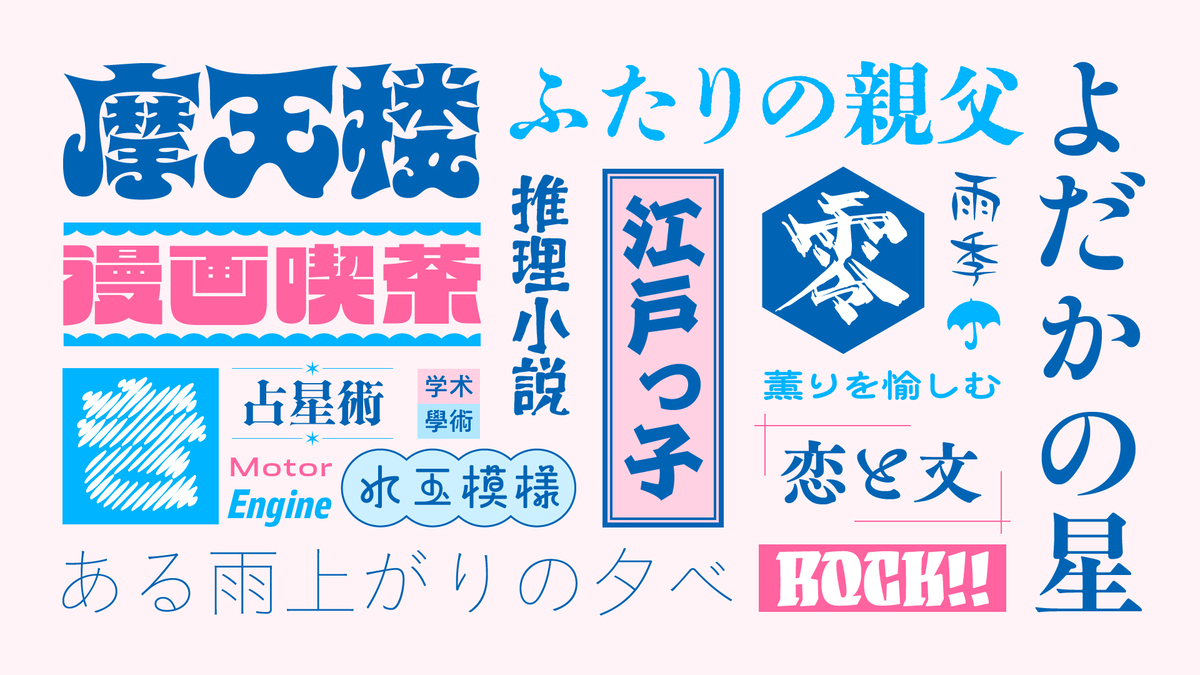
Webフォントサービス「TypeSquare」に世界観づくりにぴったりな和文デザイン書体やグローバルな情報発信にも対応できる多言語書体などの2024年度新書体を追加
モリサワは2024年10月15日から、WebフォントサービスTypeSquareに、世界観づくりにぴったりな和文デザイン書体のほか、グローバルな情報発信にも対応できる多言語書体、写研フォントなど2024年度新書体として160書体を追加したことを発表した。
2024年度新書体には、サイケデリックなアートや音楽からインスパイアされた極太の「虹蛸天国(にじたこてんごく)」のほか、丸い輪のような装飾が楽しげな印象を与える「はるかぜ」、江戸文字からインスパイアされた「てやんでぇ」など、世界観づくりにぴったりなデザイン書体をリリース。
さらに書家による毛筆の文字が元となった「花氷(はなごおり)」など、華やかな筆文字系デザイン書体の選択肢が広がる。
明朝体には、2023年にリリースした「欅(けやき)明朝 Oldstyle」の見出し書体「欅見出明朝」や、人気の「秀英にじみ」シリーズから「秀英にじみ初号明朝」などを新たに追加。
ユニークなファミリー展開が特徴の「Heavy」シリーズなど、デザインに彩りを加える特色豊かな欧文書体にも注目。
そのほか、グローバルな情報発信にも対応できる多言語フォントがより充実する。
オールドスタイルのゴシック体「A1ゴシック」に簡体字や繁体字が、欧文スーパーファミリー「Role」にインドと東南アジアの主要な種類の文字に対応する多言語展開ファミリーが、それぞれ登場。
また、ヒラギノフォントには人気書体「こぶりなゴシック」の最も細いウエイトW0を追加。
加えて、株式会社写研の代表的な書体をOpenTypeフォントとして改刻した「石井明朝」「石井明朝オールドスタイルかな」「石井ゴシック」のほか、「ゴナ」「ナール」などのバリエーション豊かな見出し書体を提供する。
UD学参丸ゴシック N Regular / Bold / Heavy
〈ヒラギノフォント〉
こぶりなゴシック W0
〈写研〉
石井明朝 L / R / M / B
石井明朝オールドスタイルかな L / R / M / B
石井中明朝 M
石井中明朝オールドスタイル大がな M
新聞特太明朝 E
石井ゴシック L / R / M / B / EB
石井中ゴシック M
ゴナ E
新聞特太ゴシック E
石井中丸ゴシック M
ナール EL / E
スーシャ H
ゴーシャ E
ミンカール H
ナミン B
いまぎょう D
いまりゅう D
イノフリー M
ゴカール H
今宋 M
スーボ B
ボカッシイG U
イナクズレ E
イナピエロ B
イナミン E
創挙蘭 E
石井楷書 M
紅蘭中楷書 M
織田特太楷書 E
有行書 D
曽蘭太隷書 B
鈴江戸 E